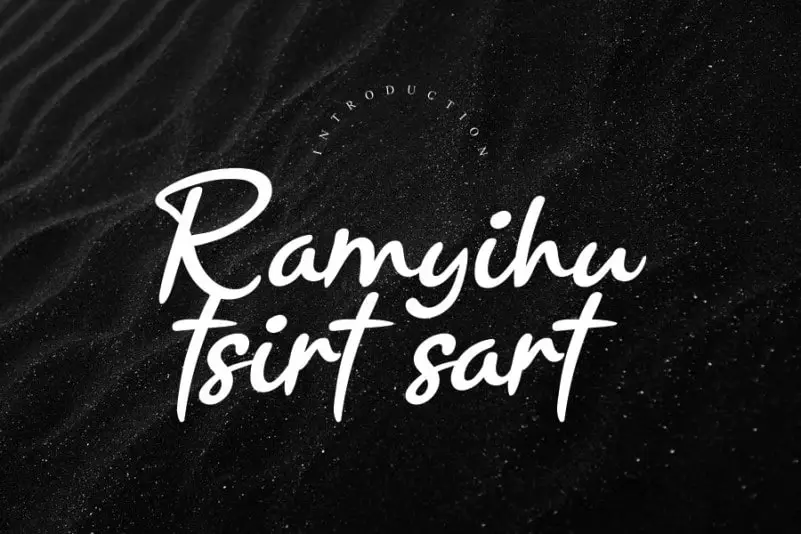
Ramyihu Handwritten Font – Download Grátis
Ramyihu Handwritten Font é uma elegante e única fonte escrita à mão, projetada para fazer seus trabalhos brilharem ainda mais. Suas características distintas a tornam versátil o suficiente para criar cartões de aniversário incríveis, arte de estação que vai doçamente embalar seu olhar, postagens no social mídia com um toque impactante e muito mais! Aproveite este belo estilo único para enriquecer suas projetos de design, tornando-os ainda mais únicos e memoráveis. Sua experiência com Ramyihu Handwritten Font certamente o levará a uma nova dimensão no mundo do design gráfico.